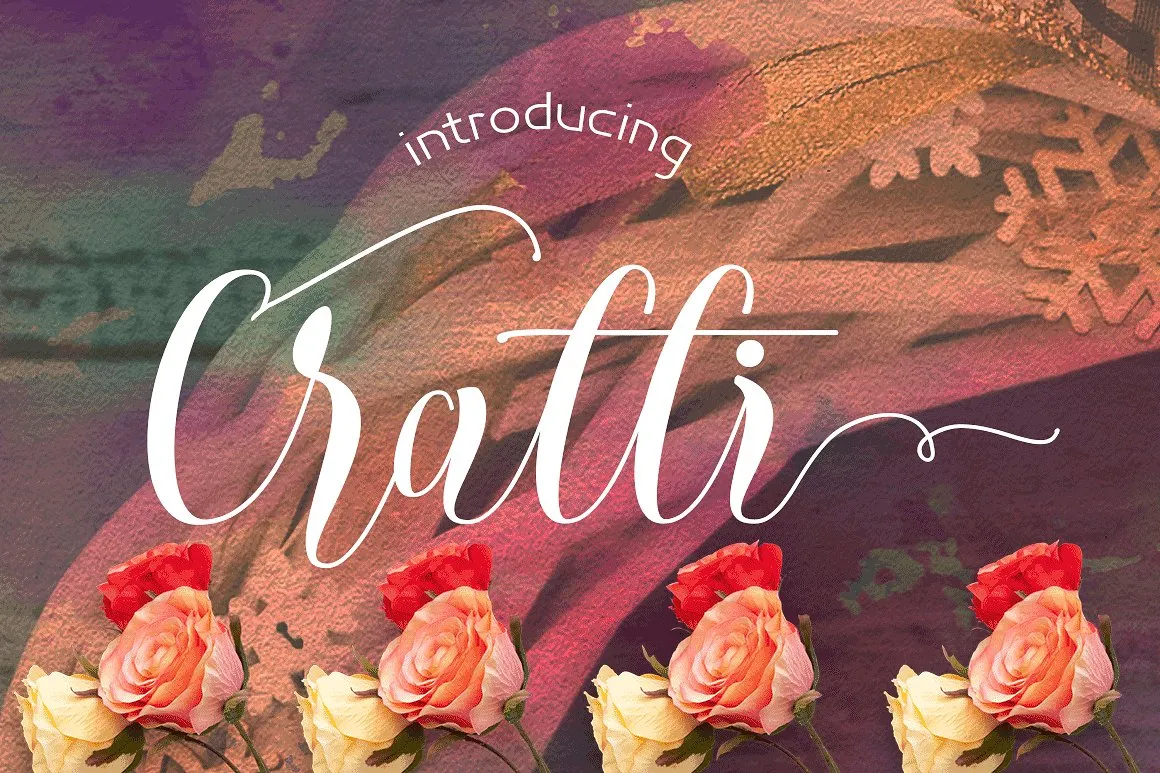
Cratti Script Font – Fonte Grátis
Cratti Script Font
A Cratti Font é uma nova adição à nossa gama de fonts para scripts modernos. Introduzida pela Hamilton, essa fonte traz a elegância e movimento das antigas aldrabas contemporâneas ao seu design. Os caracteres da Cretti dançam em torno da linha base, demonstrando uma delicadeza que transmite elegância em cada letra. Com mais de 440 formas gerais abrangendo um leque amplo de opções, a Cratti se destaca como uma fonte ideal para uma variedade de aplicações. Essa fonte apresenta recursos OpenType com alternativas estilísticas, ligações e suporte múltiplos idiomas. Suas funções variam do design de logomarca ao uso em cartões de visita e materiais de exposição, passando por rótulos de etiquetas e até mesmo camisas personalizadas ou painéis informativos para uma cerimônia de casamento. A Cretti é perfeita para qualquer projeto que precise de um toque elegante e moderno. Não hesite em explorar o poder desta fonte para adicionar profundidade a seus projetos.